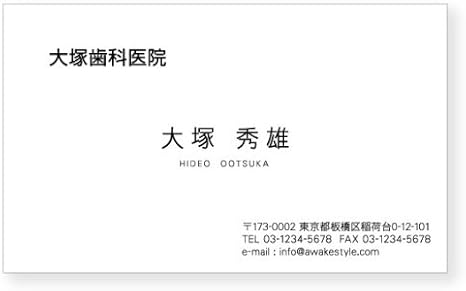
名刺 字体 おすすめ
名刺デザインと字体一覧|名刺作成のプロフェッショナル集団名刺クック Design 01 スタンダードですっきりした感じでどのようなお仕事でも通用しますね。. 名刺に使用するフォント(書体)ひとつで、相手に与えるイメージを左右します。 受け取る方は名刺デザインだけでなく、文字からも相手の職種や仕事内容をイメージすることがあります。 よって、相手に印象を残す名刺を制作する場合、デザインとともに使用フォントも気にしておいたほう. 日本で一番広く使われている明朝体。しなやかで 品格のある落ち着いたスタンダードな書体です。 楷書体 明朝体 ゴシック体 丸ゴシック体 教科書体 隷書体 作成番号 s-013m 作成番号 s-006m 作成番号 s-012m 作成番号 s-011m 作成番号 s-005m 作成番号 s-004m.